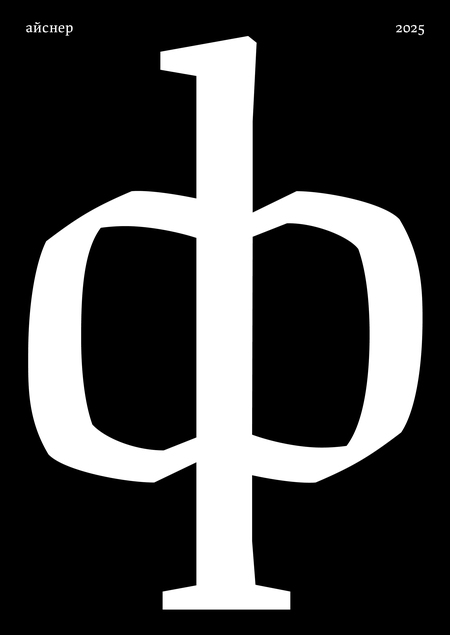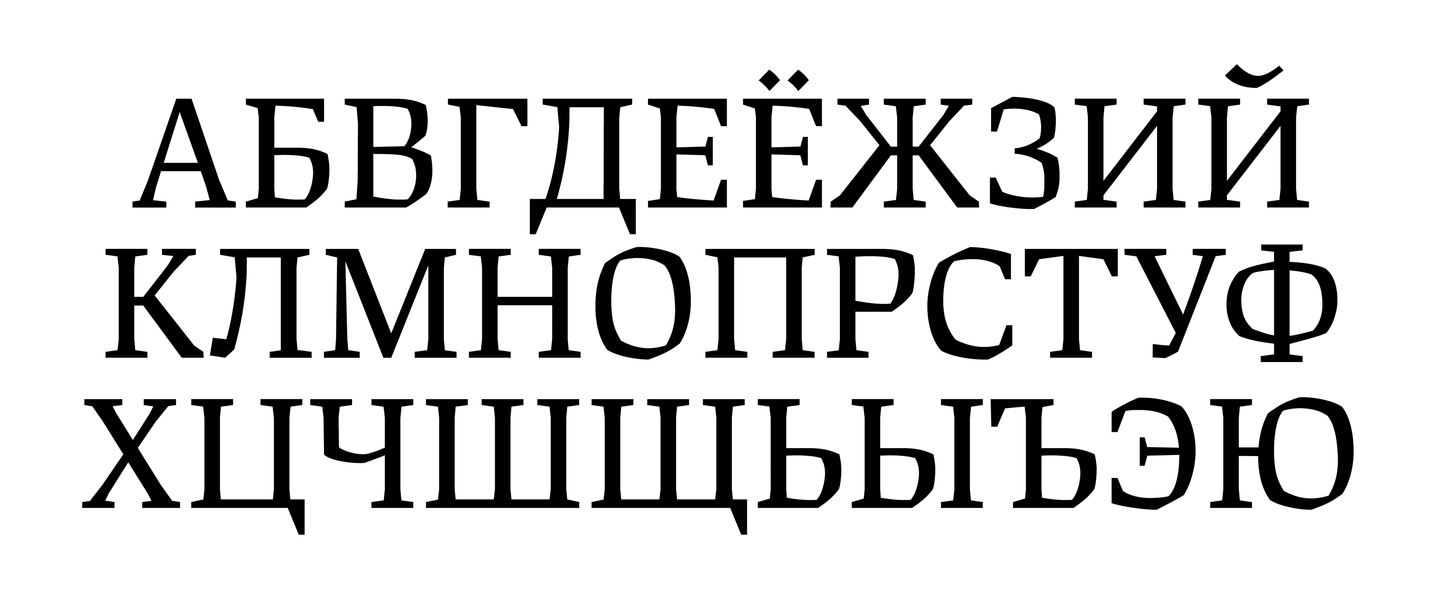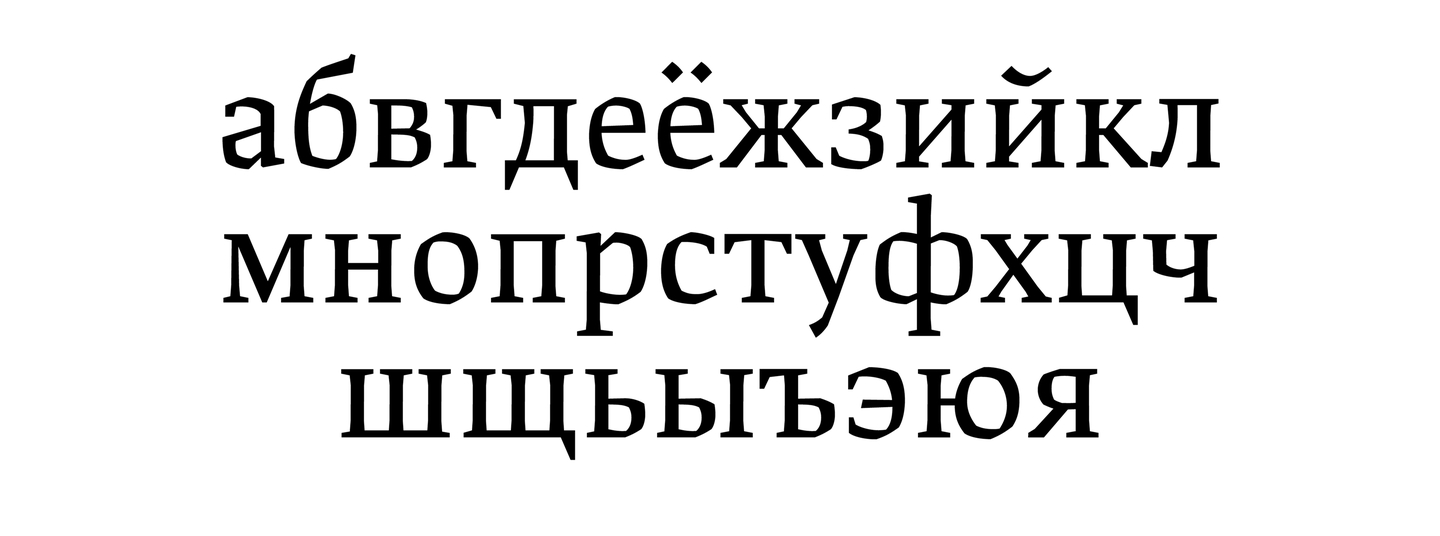
Eisner — это современный текстовый шрифт, основанный на принципах письма ширококонечным пером. Из-за особенности истории развития кириллицы, у нас до сих пор нет широкого выбора текстовых гарнитур на каллиграфической основе, хотя в латинице логика ширококонечного пера является формообразующей с первых веков нашей эры. Она лежит в основе европейского готического письма и наборных ренессансных антикв, несколько столетий развивалась в русской рукописной культуре и проявилась во множестве уникальных книжных почерков. В шрифте Eisner привычные современному читателю формы выстроены так, как если бы их создавал средневековый мастер, пользуясь цифровыми инструментами.
При письме ширококонечным пером максимальная толщина приходится на участки, соответствующие примерно 13 и 19 часам, что обусловлено наклоном пера и направлением движения руки. Это важно при проектировании шрифтов на основе ширококонечного пера, поскольку позволяет воспроизвести характерные особенности штрихов и их контраст.
Изломанность форм и решительность линий роднит Eisner с чешским и немецким экспрессионизмом.
В рамках дипломного проекта, посвященного созданию современной кириллической текстовой гарнитуры, основанной на принципах ширококонечного пера, подготовлен буклет, демонстрирующий работу шрифта в наборе. В качестве материала для вёрстки выбрано эссе Геррита Нордзея, впервые опубликованное в его бюллетене LetterLetter (выпуск 7 за 1988 год), который он писал от руки для ежегодной конференции ATypI.
Геррит Нордзей (1931– 2022) — выдающийся нидерландский типограф, каллиграф и педагог. С 1960 по 1990 год возглавлял кафедру шрифтового дизайна в Королевской академии искусств в Гааге. В своих работах сформулировал теоретическую модель, соединяющую движение, направление и угол наклона инструмента с формой букв. Эта модель стала основой его подхода к анализу письма и типографики и оказала значительное влияние на развитие современного шрифтового дизайна.